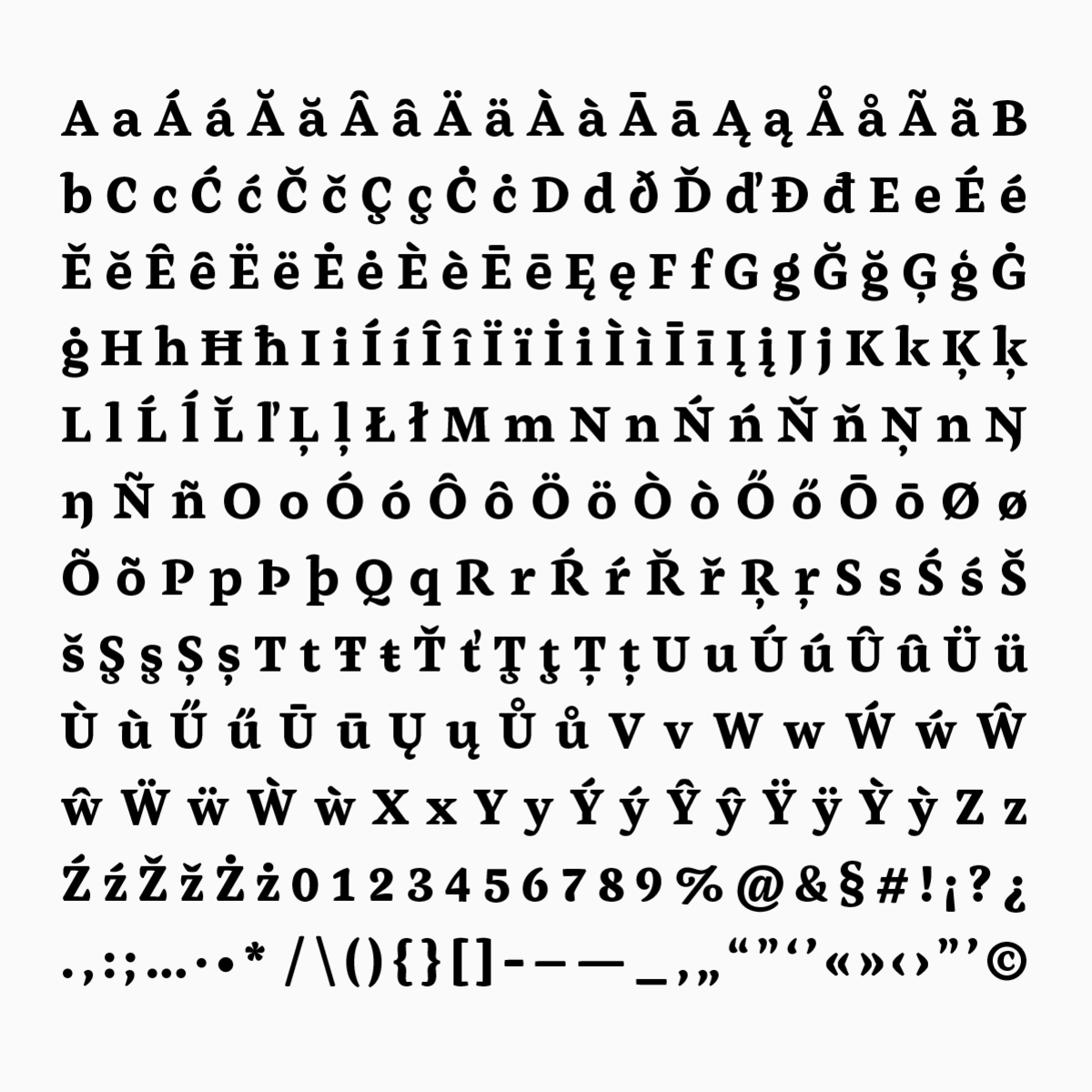
Henk Work Font
Henk a commencé pendant mes études au master Type Media au KABK comme projet final. Henk a été conçu comme une famille d’au moins 6 styles avec deux personnalités différentes. Henk Out et Henk Work. Henk Work est une police de caractères intelligente et travailleuse conçue pour la rédaction de longs textes juridiques qui contiennent souvent de nombreuses abréviations et chiffres.